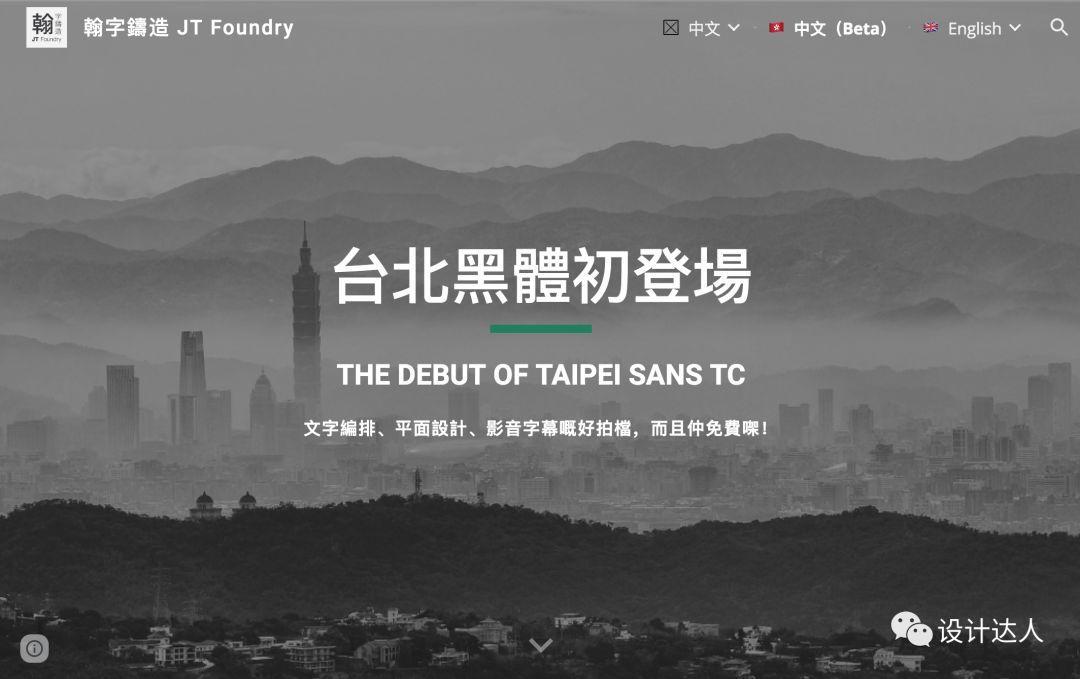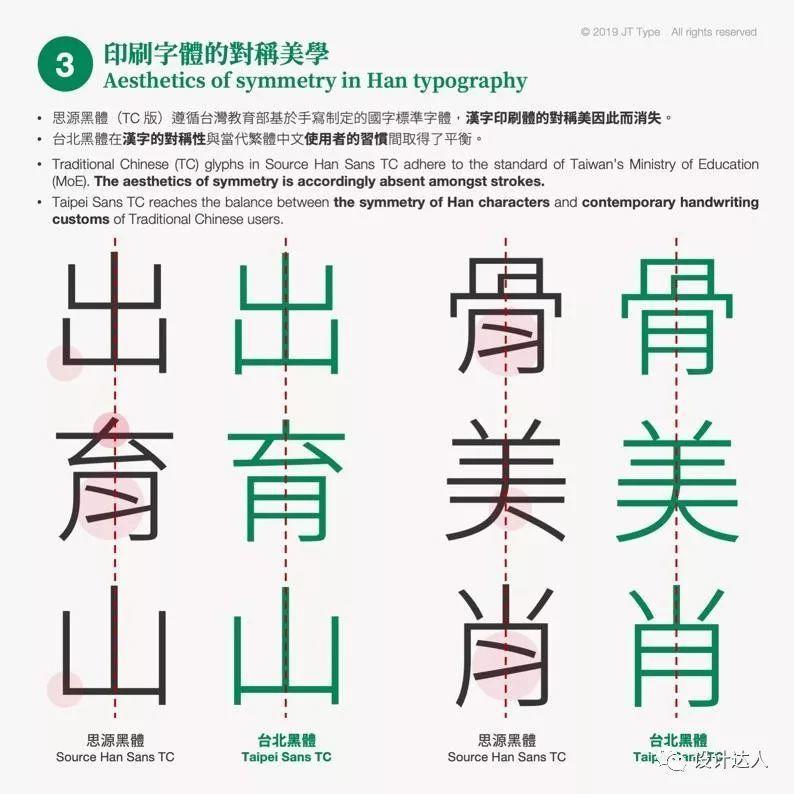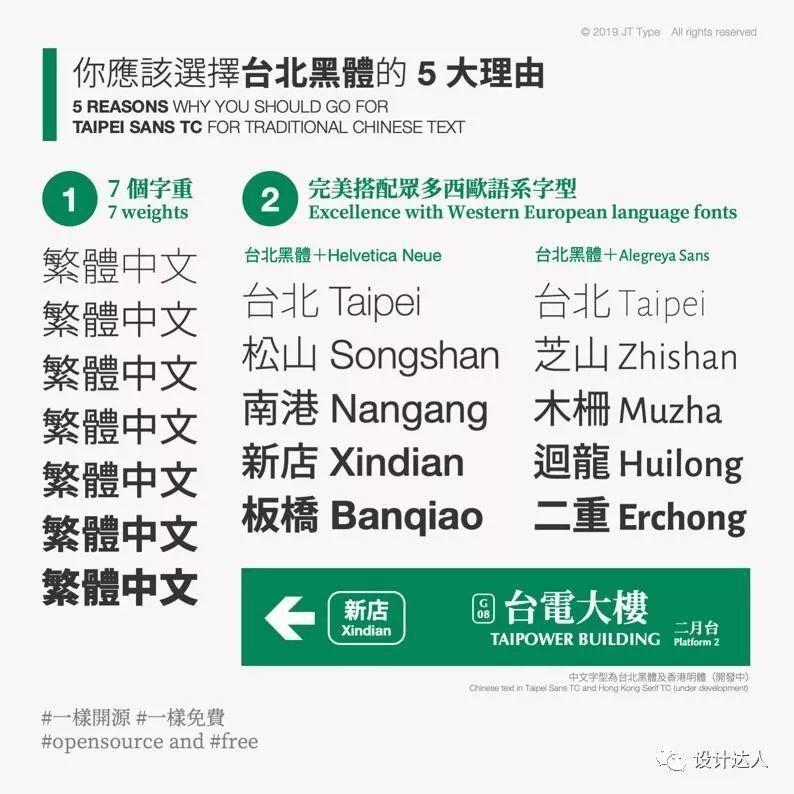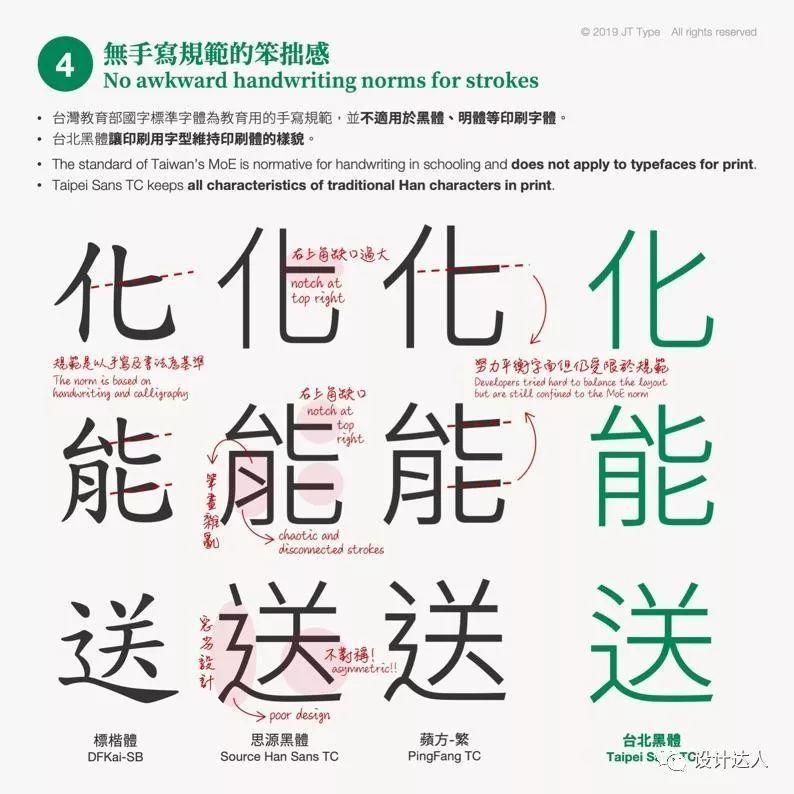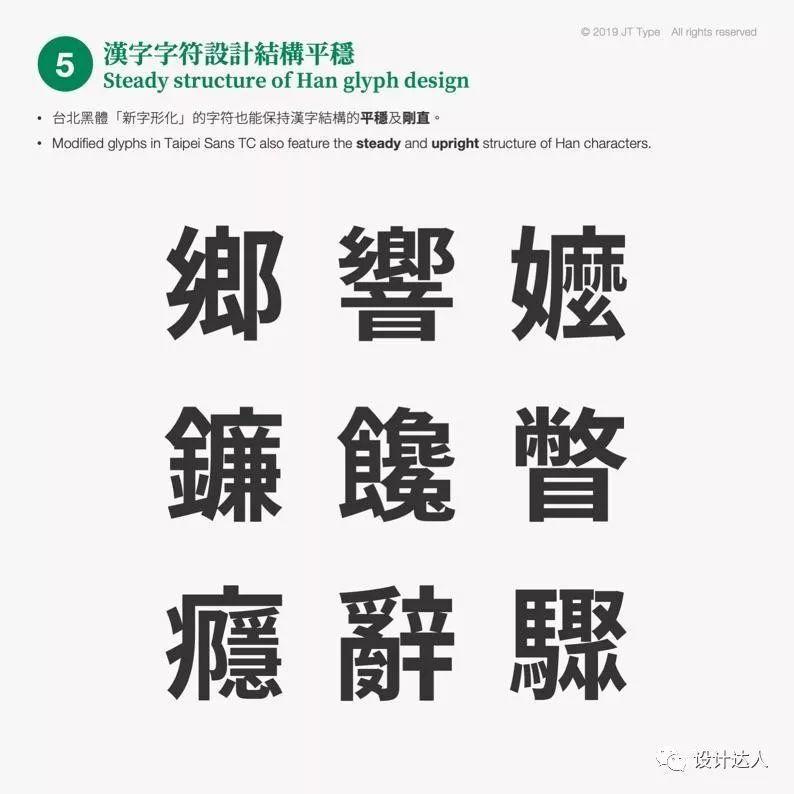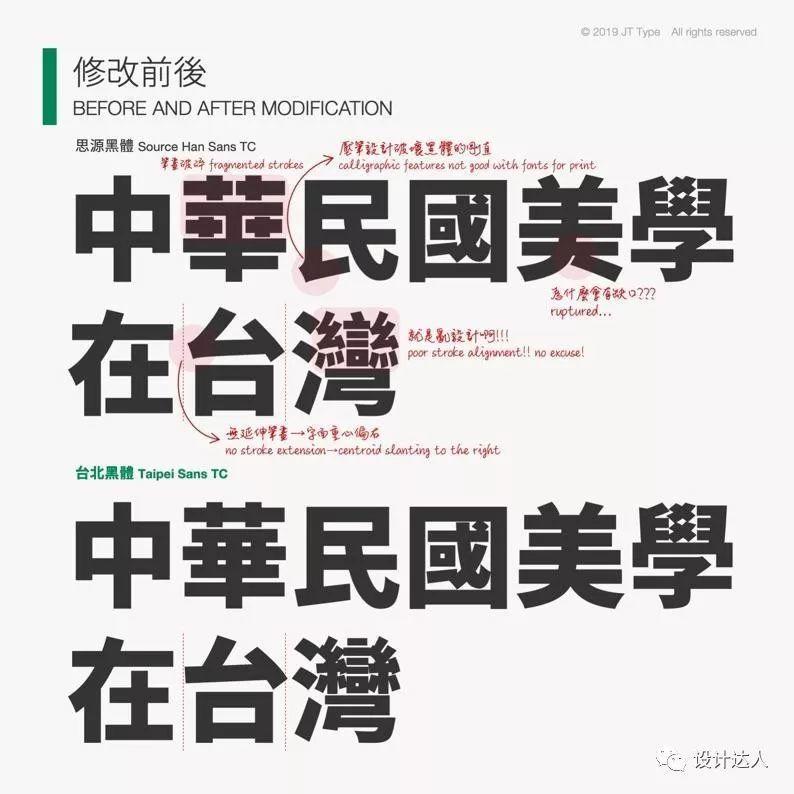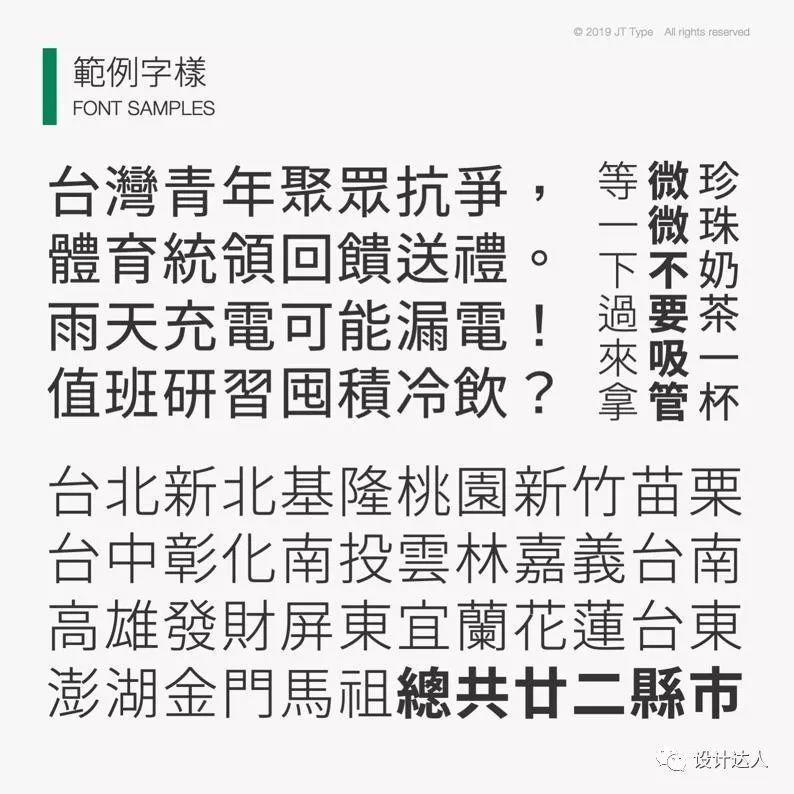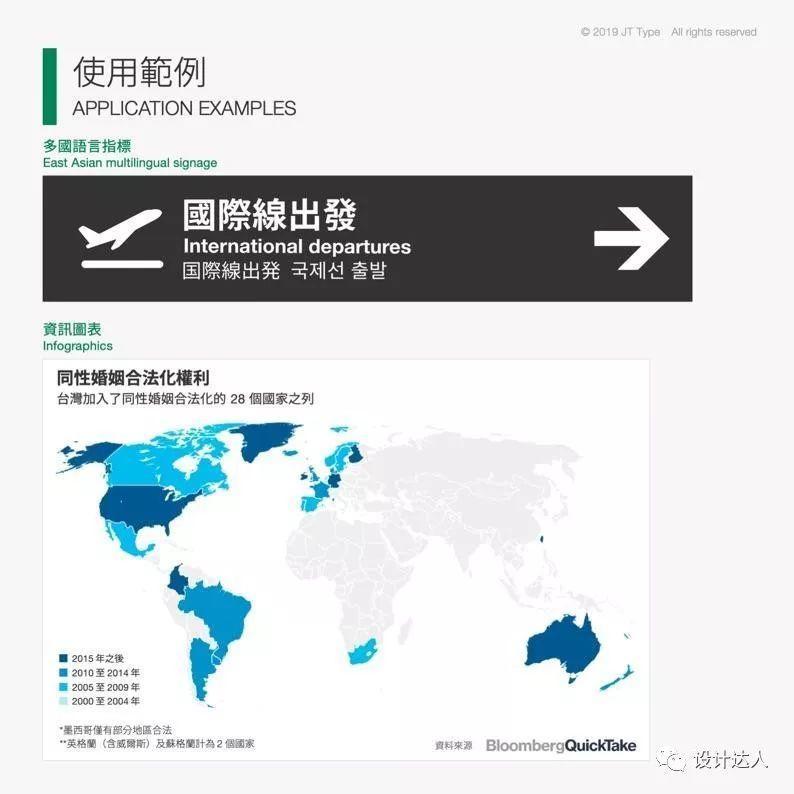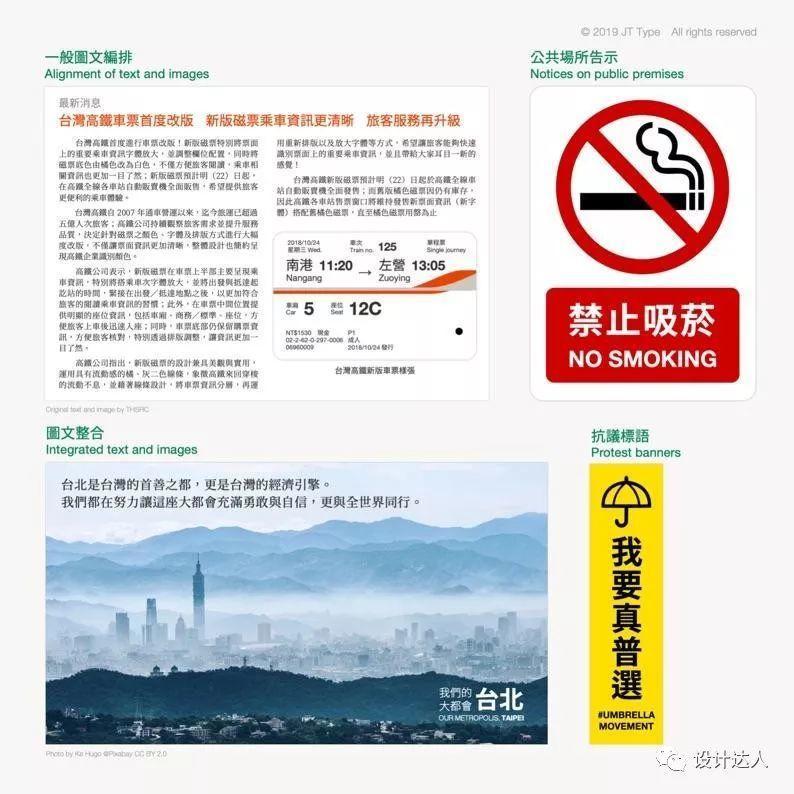
一款免费的繁体字体台北黑体
台北黑体(Taipei Sans TC)是最近新出的一款繁体字体,由「翰字鑄造」制作,适用于文字排版、平面设计、影音字幕以及平面印刷类的设计使用,而且是免费个人及商业用途。
为何制作台北黑体?
免费的中文字体数量并不多,可用于印刷的字体多数需要版权,使用者需要支付费用才能使用。而很多用户反馈思源黑体和思源宋体的繁体其实有好多设计问题,甚至不太适合在印刷场景使用。
因此翰字鑄造开始以思源黑体为基础,改造成适合平面印刷用的黑体繁体字型。
字体特色
经过优化后的台北黑体,变得更适合平面印刷用途。
使用范例
通过一些标示、资讯图表、公告的范例展示该字体的使用场合。
目前台北黑体拥有三个字重 light、regular、bold,而预计2020年底前推出剩余的字重 extralight、normal、medium、heavy,以满足种类设计的需求。